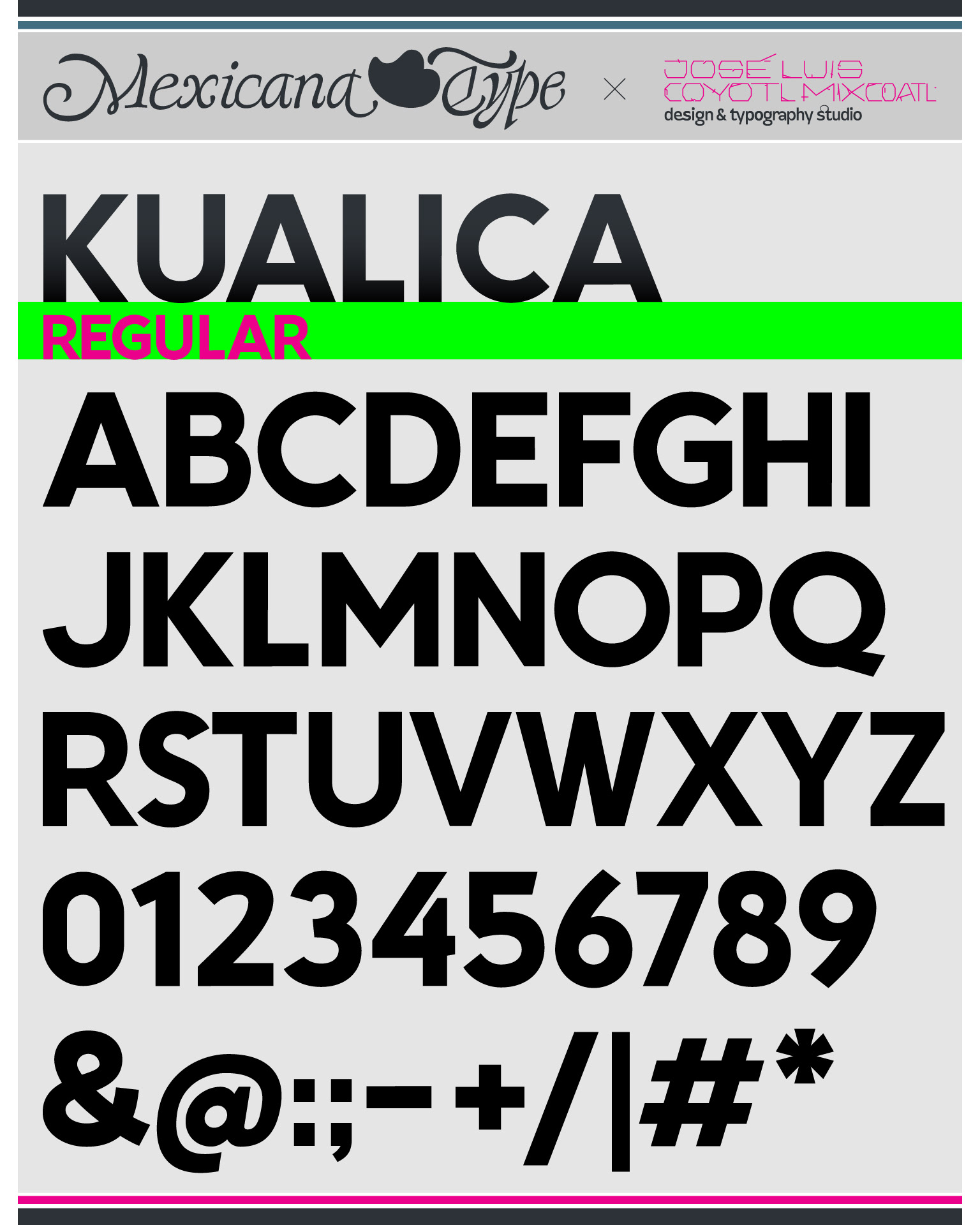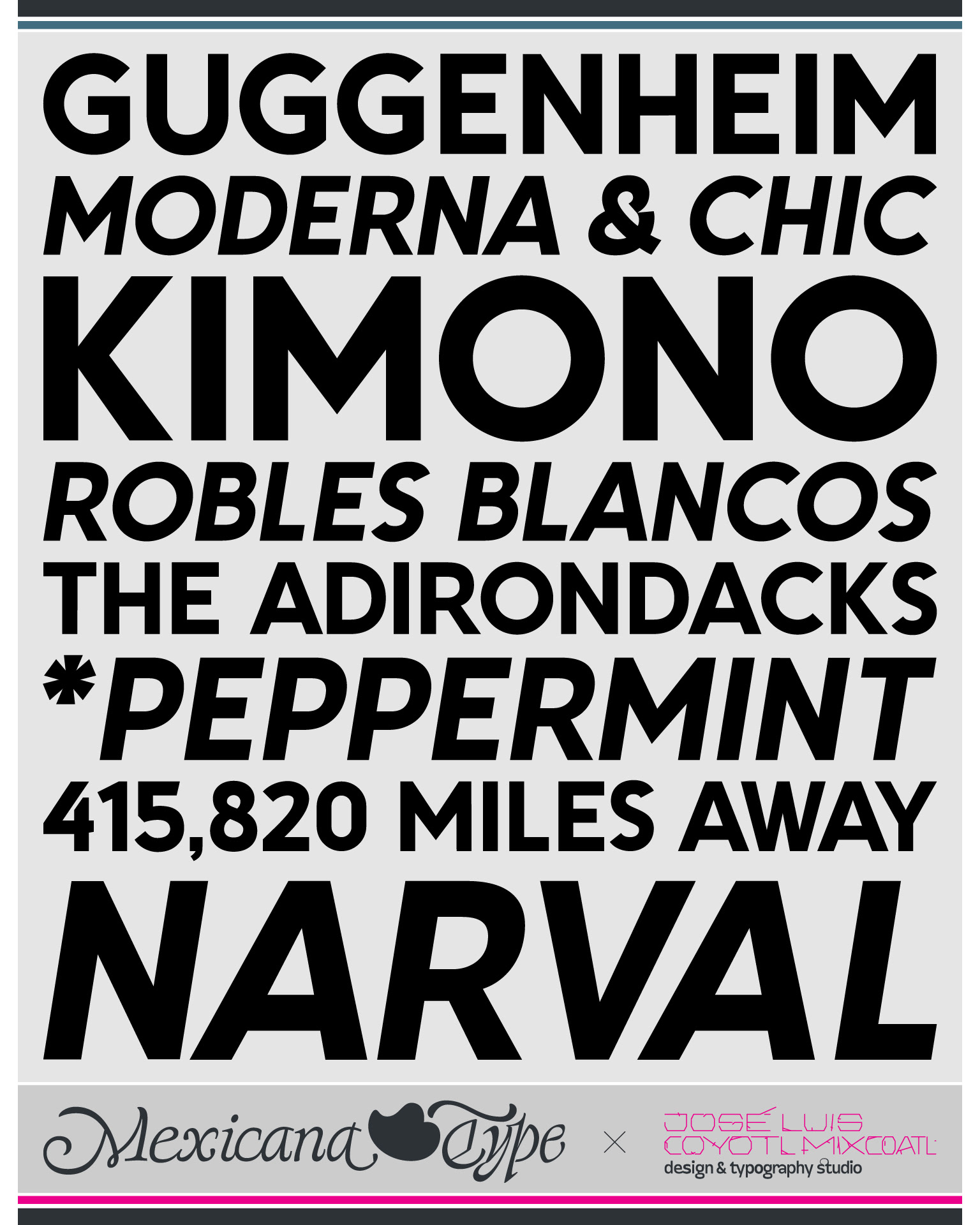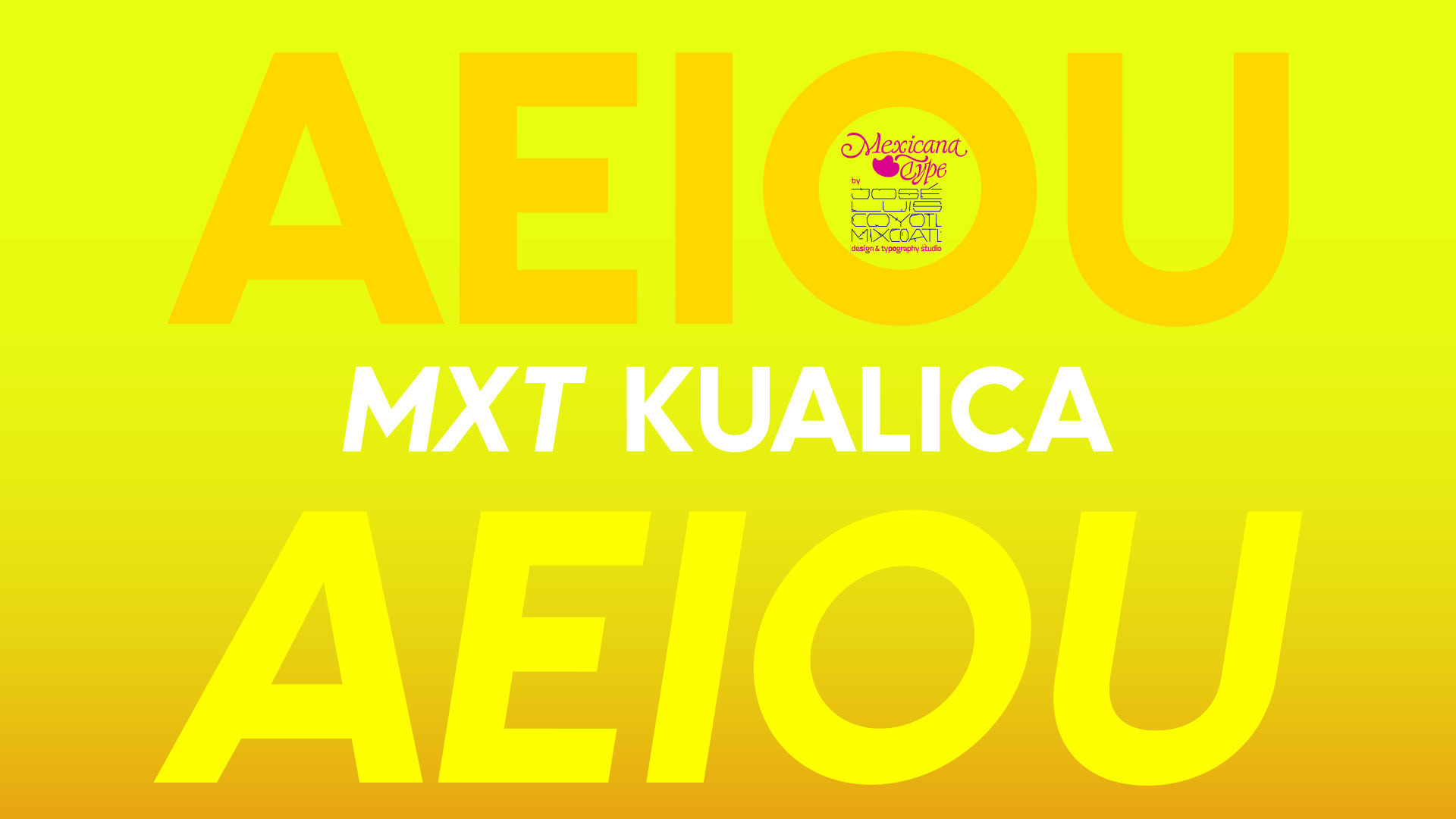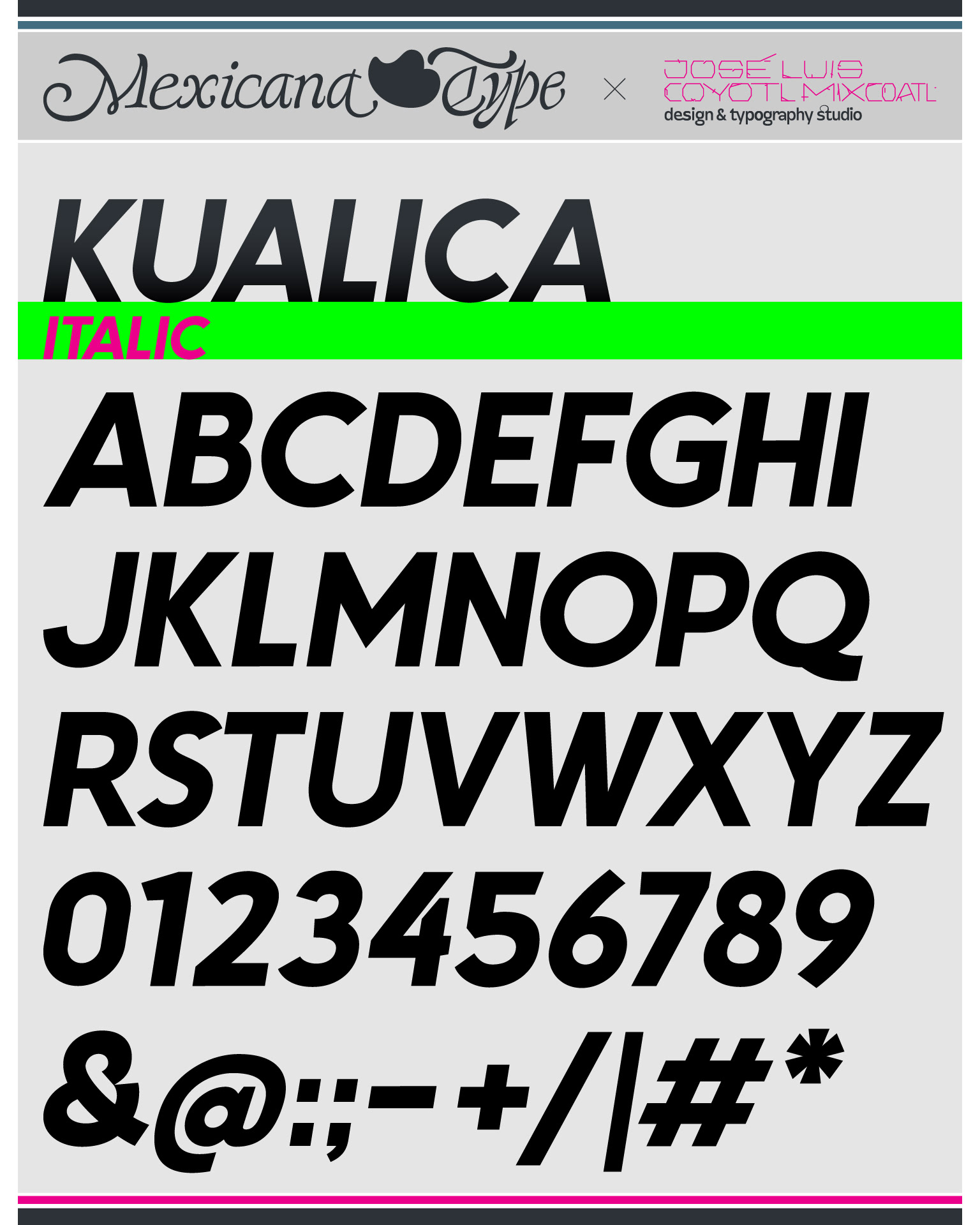
MxT Kualica inició como un custom type originalmente desarrollada para la exploración y composición de una marca tipográfica, que aunque pudiera parecer un estilo similar a otras fuentes tipográficas en el mismo sentido geométrico y moderno, las singularidades que se desarrollaron llevaron a más adelante ampliar su mapa de caracteres, a retrabajarla para que funcionara en un cuerpo de texto menos display que el de un logotipo, con un trazo más uniforme y mejor estructurado que permitiera utilizarla en otros proyectos con cuerpos de textos un poco más amplios que permitieron el desarrollo de un set de mayúsculas/altas, números, y algunos signos adicionales en dos variantes: Regular e Italic.